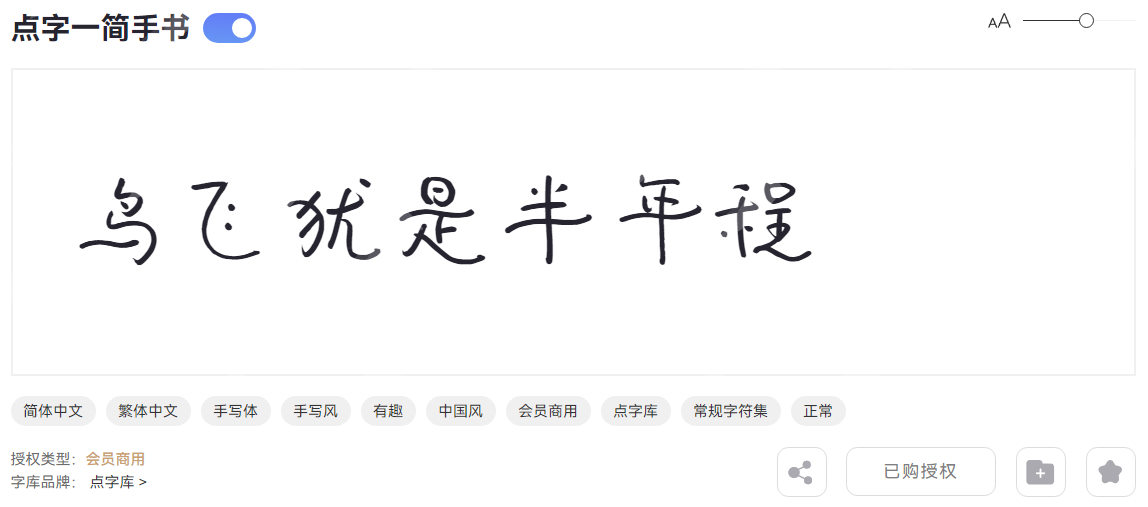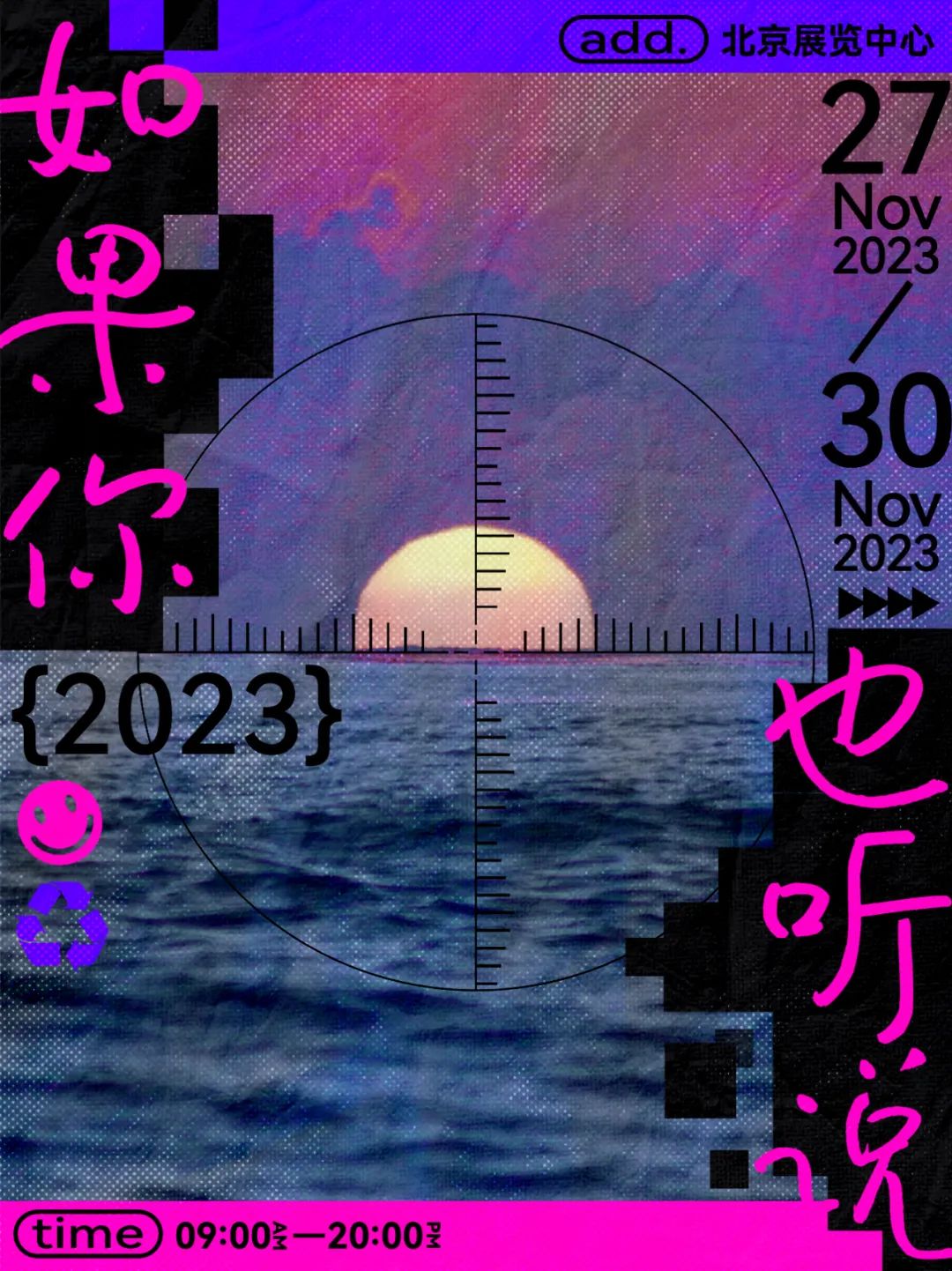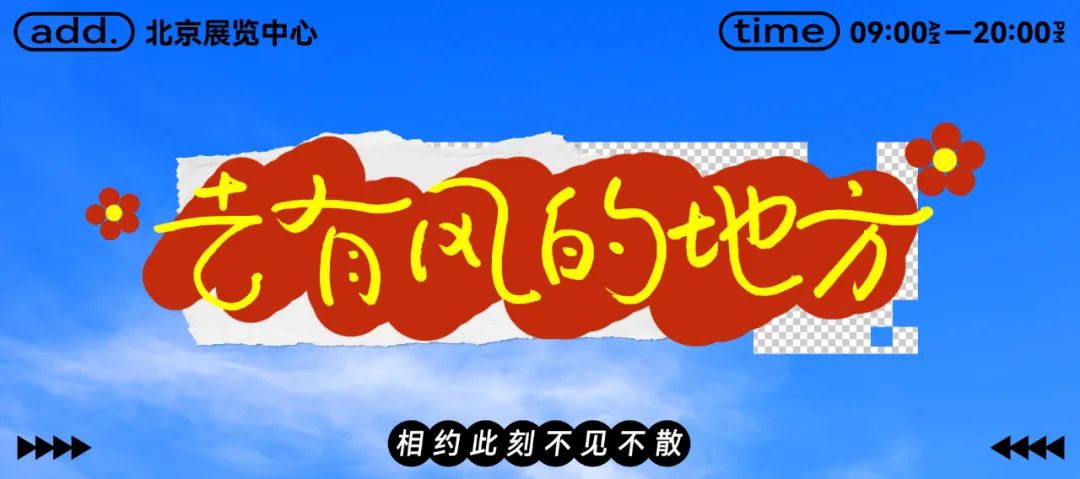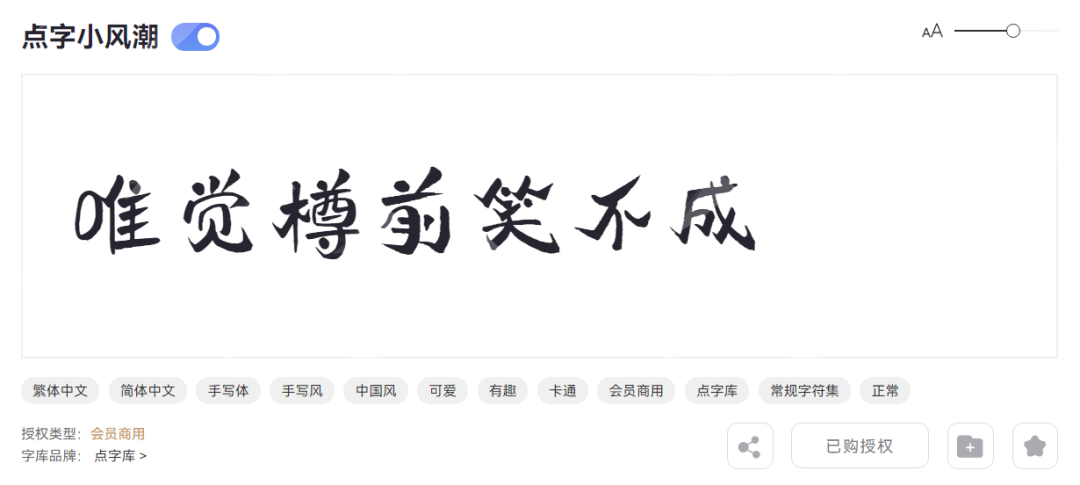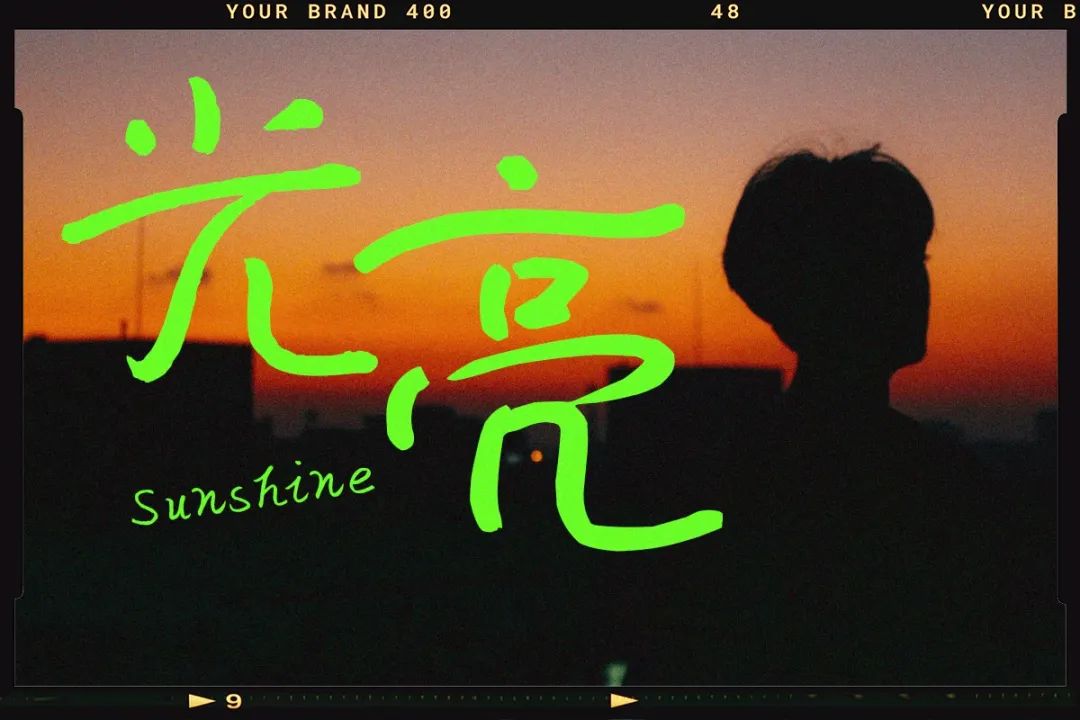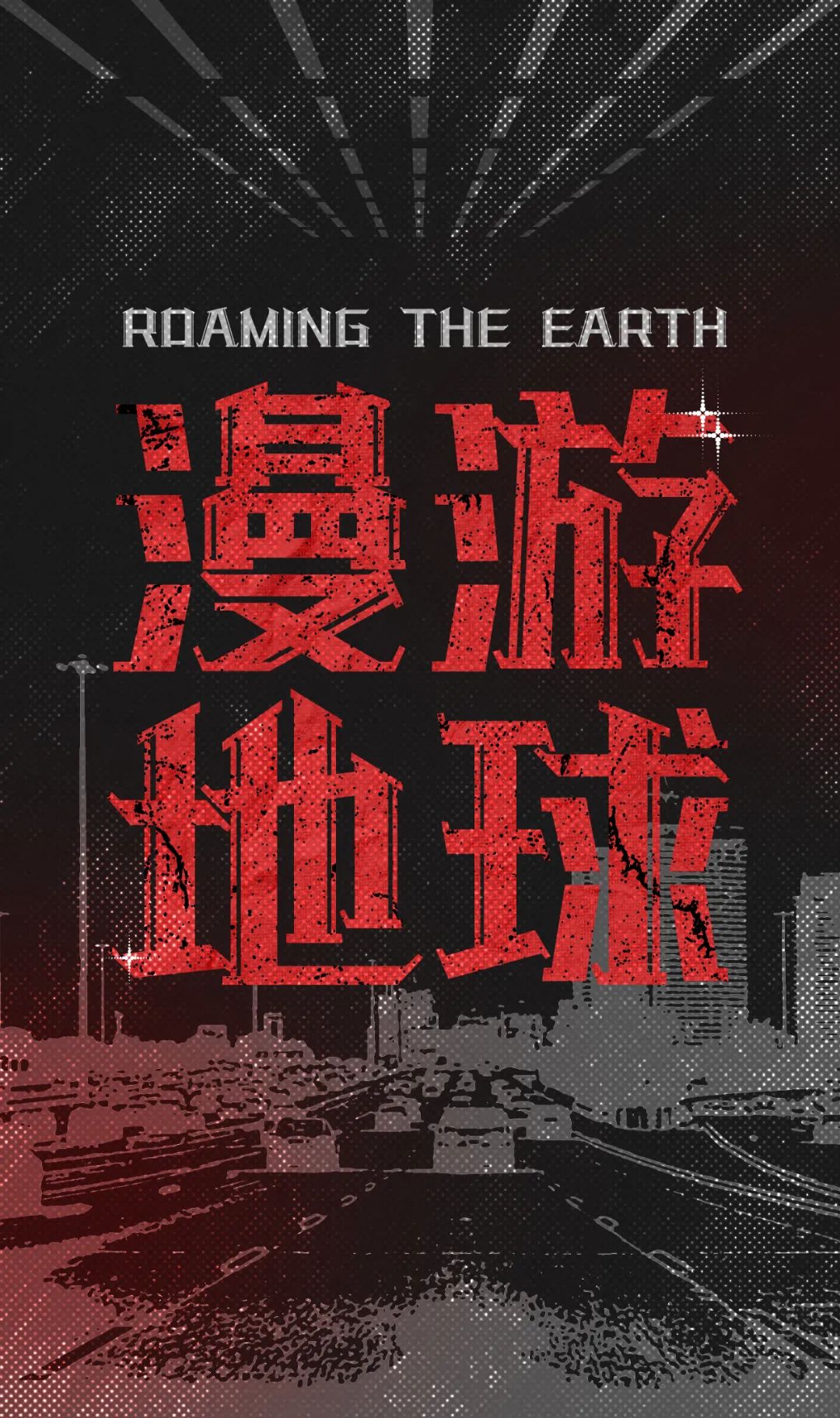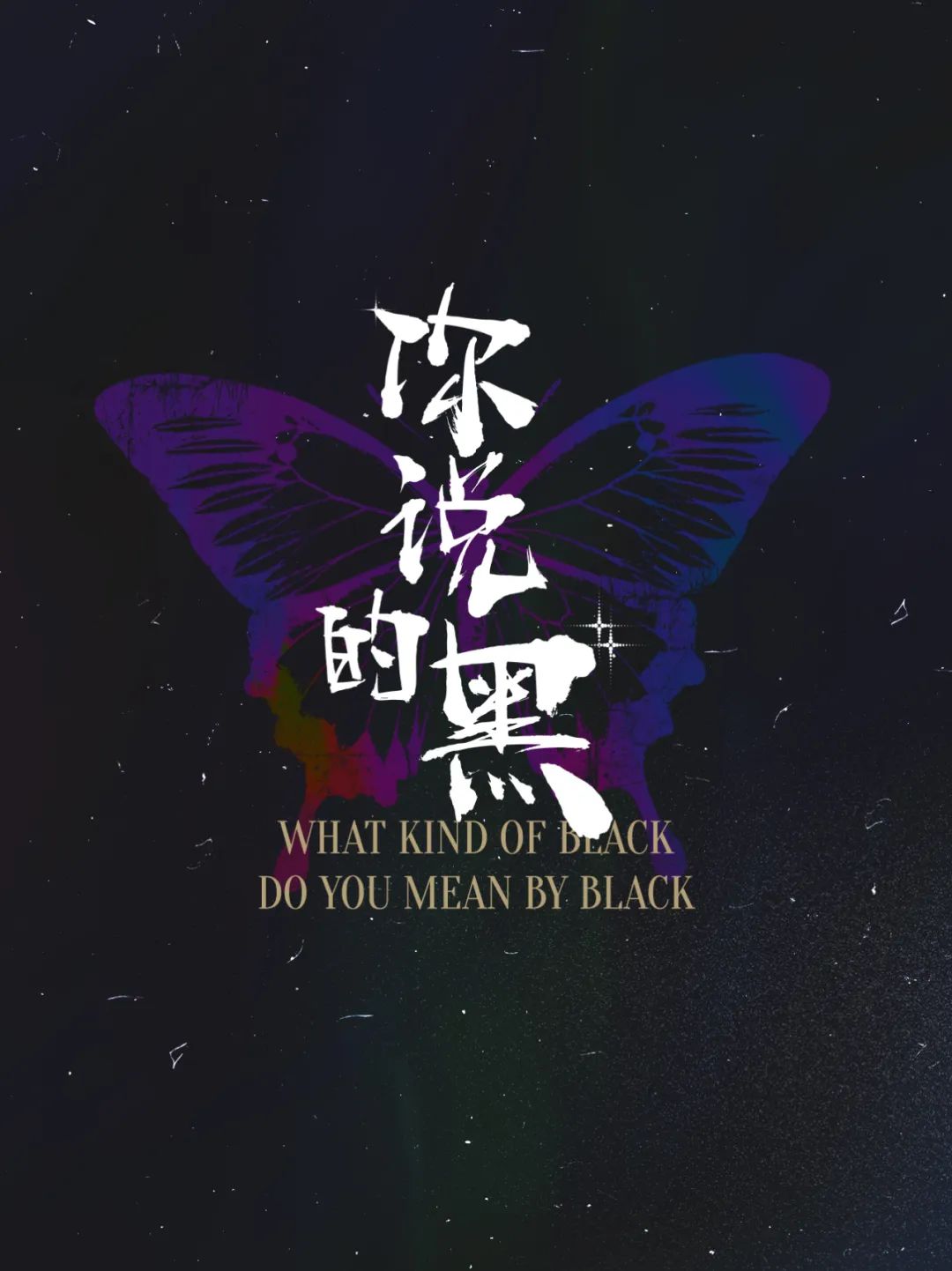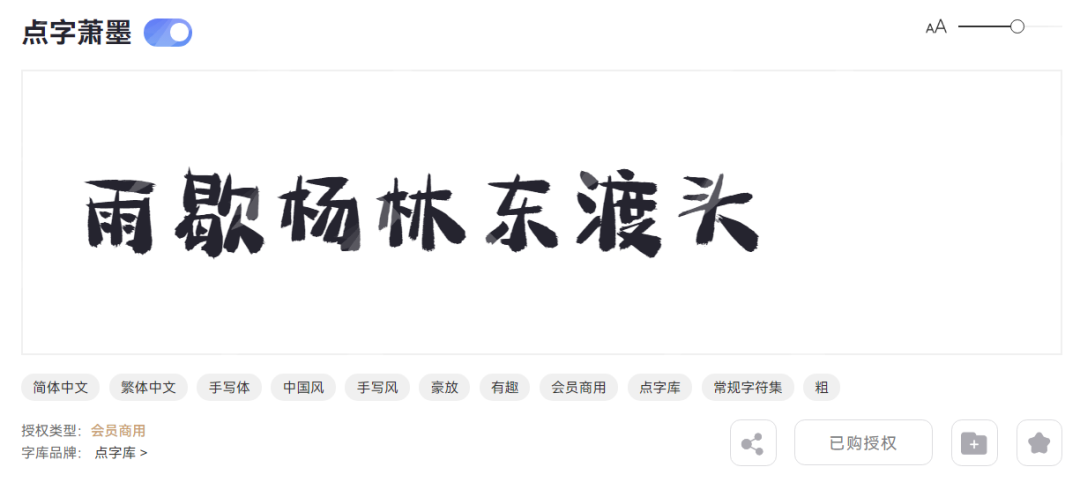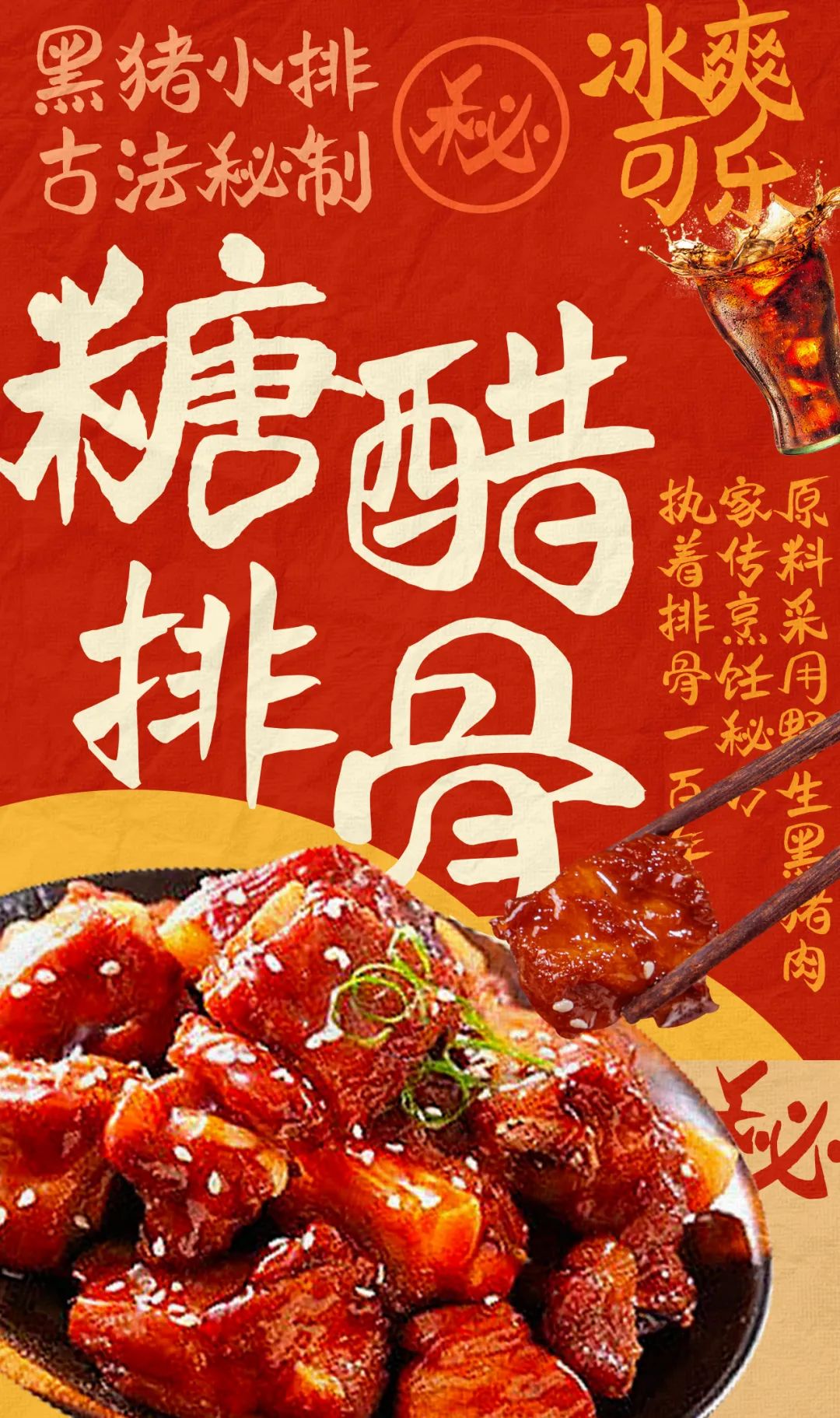
点字一简手书
看到这款字的第一眼,就被它迷住了,因为很浪漫,又有一种诗和远方的松弛感,预感会爆!
点字小风潮
小风潮最大的特点是,看似桀骜不驯,实则有迹可循, 既可以现代,也可以古风。
点字专辑体
继点字飒爽手写体之后,又一款适用于音乐专辑的字体,还加入了哥特风装饰,非常好用。
点字藏锋
算起来,霸道潇洒的手写字已经不少了,只是每一款“英雄”,都有自己的独门绝技。
点字萧墨
点字萧墨虽然是手写字,但它是偏亲和力的那种,做标题字很不错。
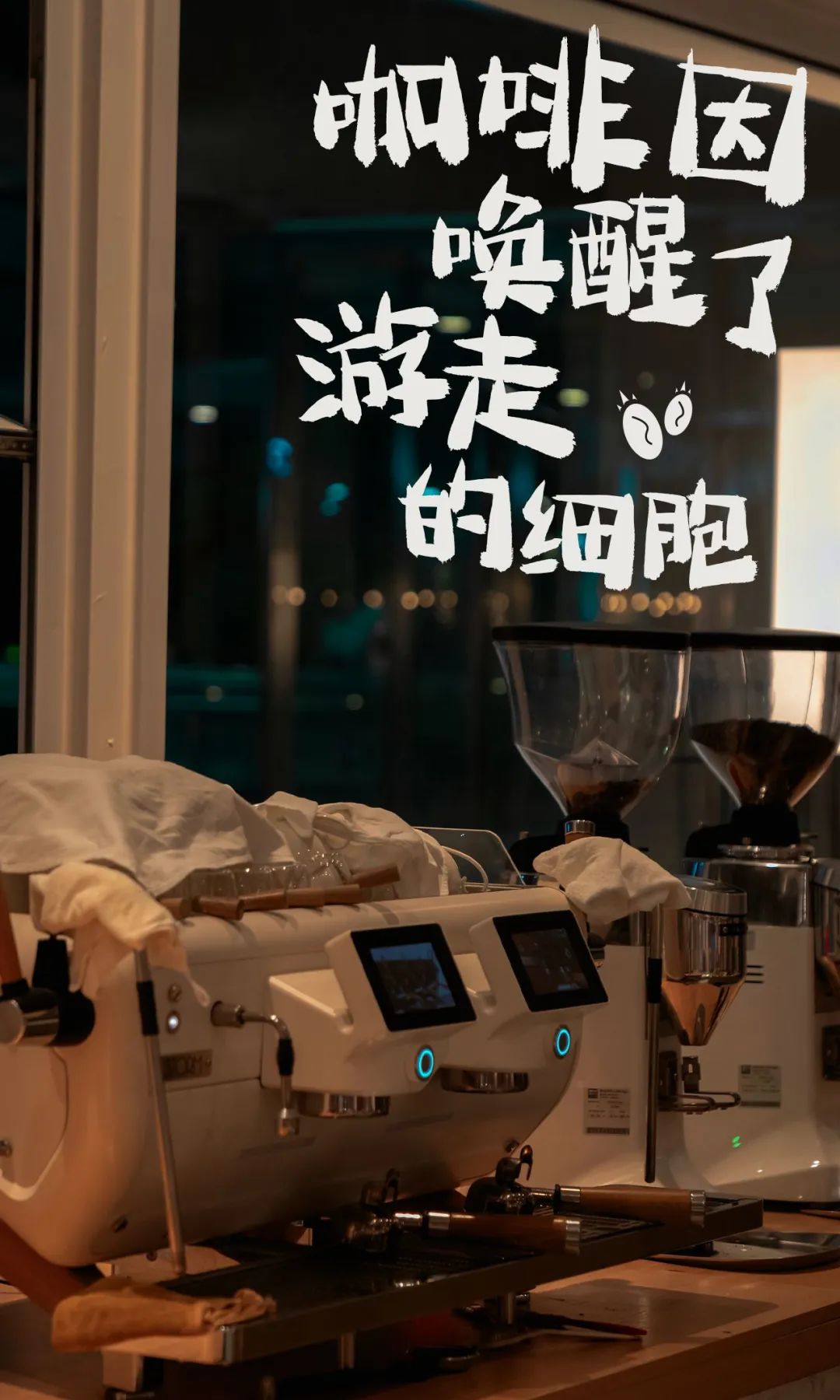
点字清丽仿宋
清丽仿宋正如它的名字一样,又清新又秀丽,用在哪里都自带高级感。
点字倔强圆家族
当点字倔强黑变温柔了,看起来还挺有“萌”的,一共有7款字重。